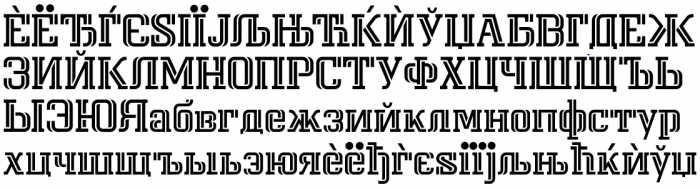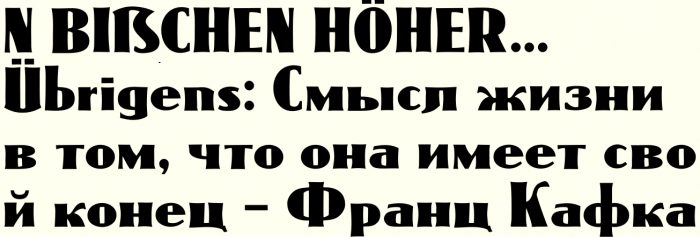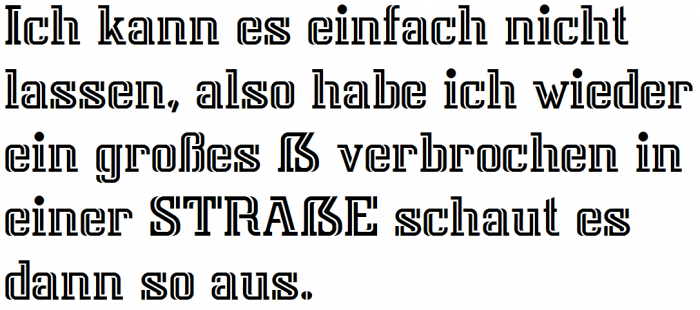
Hübsch. Der Innenbogen berührt optisch fast den Stamm. Vielleicht orientiert man sich da an den anderen Minimalabständen und gleicht das hier entsprechend aus?
Ich frage mich auch, warum der Bogen so weit oben ist, das gibt einen arg kleinen Binnenraum?! Die Betonung ist dadurch sehr weit oben, was bei den anderen Zeichen nicht der Fall ist. Wenn man den etwas tiefer und weiter nach rechts schiebt kann man dem wohl entgegenwirken ..?
'n Büschen weniger – die Form des S darf ja ruhig erkennbar bleiben, aber ohne dass es oben zu eng wird.
Ich finde es sehr sehr schön eigenständig und gut lesbar – in meinen Augen keine Verwechselungsgefahr vorhanden. Das wäre eine famose Schrift für einen Geigenbauer. :biglove:
Meine Frage: Geht das für die "Attic" ?
Funzt m.E. sehr gut. (Besser als der i-Punkt und die Schwungbögen unten rechts bei m und ß.)
Der i-Punkt war mir auch etwas ulkig, aber ich wollte eben die Originalschrift aus den 1880ern nicht nachbessern in der Hinsicht, hier vorgegebenes zu ändern und das gilt dann auch für die rechten Bögen bei h,n, m, den ich dann, um passend zu bleiben, auch fürs ß genommen hab.
BTW Was sind das für Ulkige Größenangaben: Long Primer für 10 Punkte, Great Pprimer für 18 Punkte usw. Wo kommen diese her?
Der i-Punkt war mir auch etwas ulkig, aber ich wollte eben die Originalschrift aus den 1880ern nicht nachbessern
schreib mal bitte was zur quelle.
woher stammt die schrift, wer hats erfunden?
Und hier ein Fundstück, das gerade der Moderator einer meiner Xing-Gruppen gepostet hat zum Thema Versal-Eszett (aus einem Anzeigenblatt in Lauenburg):
Ach ja, solch eines hab ich auch... Die aktuelle Werbung eines Bleiche-Pulvers, das ich mal verpixelt hab, schließlich will ich hier keine Werbung machen (mit Ausnahme der fürs ẞ)